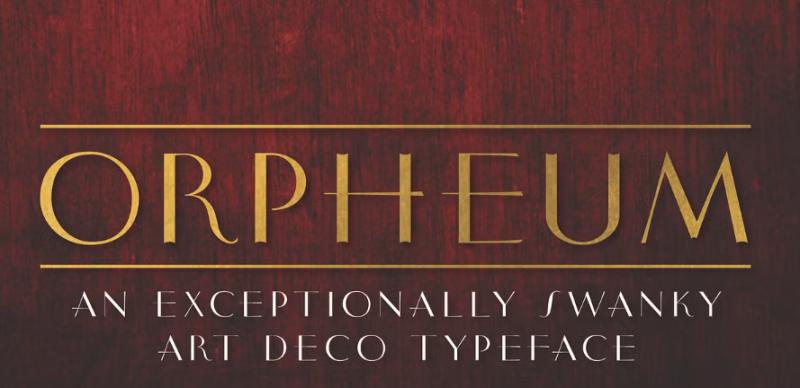
[Creativefabrica] Orpheum Font (StudioWorks)
Orpheum - это крутой, смелый и современный дисплейный шрифт. Какой бы ни была тема, этот шрифт станет прекрасным дополнением к вашей библиотеке шрифтов, поскольку он может улучшить любое творение.